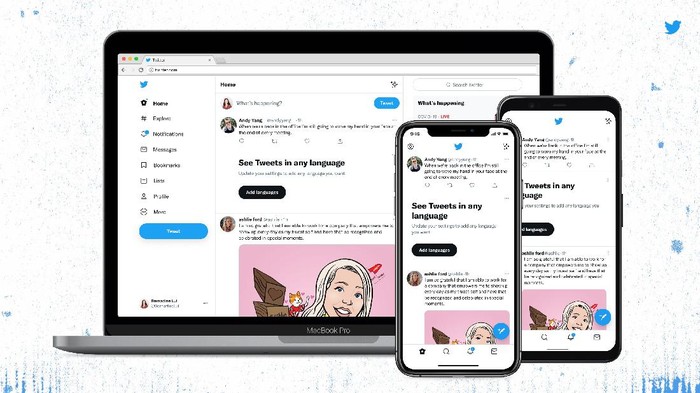
Teknologi.id – Twitter merombak
desain web-nya dan mengenalkan font baru bernama Chirp. Hal ini langsung disambut
para pengguna Twitter dengan kebingungan. Beberapa di antaranya ada yang protes
akan font baru Twitter membuat mereka pusing.
Pihak Twitter menjelaskan, font Chirp
ini sebenarnya telah hadir sejak Januari 2021. Sebelumnya, Twitter selalu
mengandalkan typeface seperti SF Pro, Roboto dan Helvetica Neue.
Ketika debut di bulan Januari, font
Chirp ini digunakan guna kebutuhan promosi dan grafis, tapi belum dipakai
sebagai font utama di aplikasi atau feed. Sekarang, Twitter menjadikan font
Chirp sebagai font utama di web, mobile web, aplikasi Android dan iOS.
Twitter juga menjadikan teks cuitan yang ditulis dalam bahasa Barat menjadi rata kiri. Pihak Twitter menjelaskan perubahan ini dibuat guna cuitan bisa lebih mudah dibaca sambil scrolling layar.
Perubahan paling mencolok ada di Twitter
versi website. Warnanya kini dibuat lebih high-contrast begitu juga dengan
tombolnya. Latar belakang abu-abu dan garis pemisah juga berkurang.
Salah satu perubahan terbesarnya
adalah warna biru yang menjadi ciri khas Twitter justru berkurang. Misalnya,
cuitan dan ikon navigasi kini berubah menjadi warna hitam saat menggunakan tema
Twitter default dengan latar belakang putih.
"Kami memperbarui warna kami
menjadi kontras tinggi dan warna biru jadi lebih sedikit -- perubahan yang
dibuat untuk menarik perhatian ke foto dan video yang kalian buat dan
bagikan," ucap pihak Twitter melalui akun @TwitterDesign.
Twitter mengatakan akan meluncurkan
warna baru dalam waktu dekat. Namun, tidak diketahui dengan pasti apa maksud
mereka.
Netizen yang sudah melihat tampilan
baru Twitter pun langsung ramai membahas perubahan desain ini. Saking ramainya,
kata kunci 'Font' trending di Twitter sejak Kamis sore.
Sebagian pengguna ada yang kaget melihat tampilan baru Twitter, ada juga yang merasa aneh melihat beberapa huruf yang digunakan. Bahkan ada juga yang mengeluh sakit kepala dan kesulitan membaca font baru Twitter tersebut.